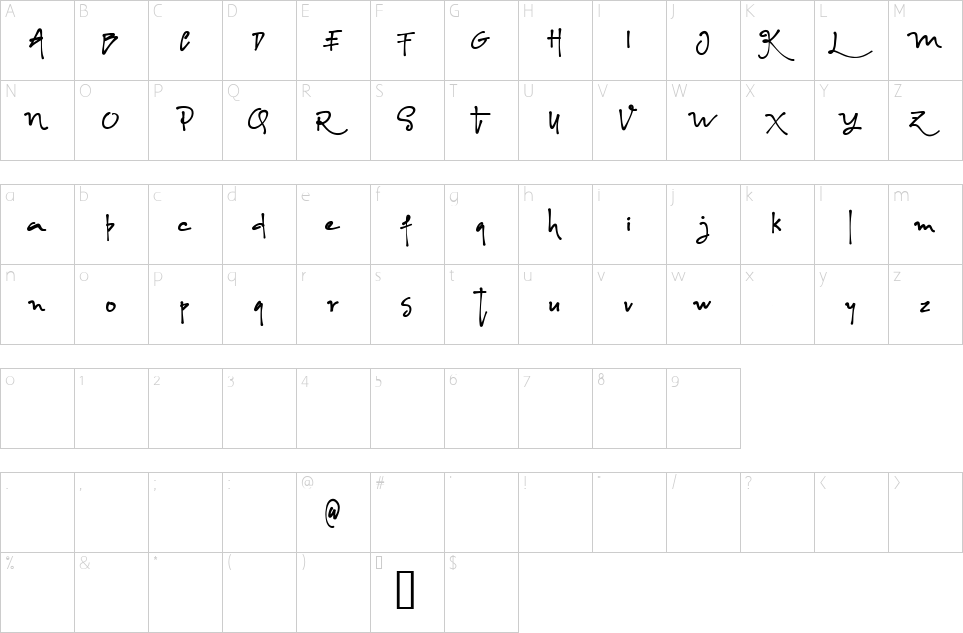
Esta fonte ‘Albanian Typeface’ foi projetada pela designer Selawe e é uma das opções gratuitas disponíveis para quem busca fontes modernas e elegantes. Com traços finos e linhas levemente arredondadas, esta fonte é adequada para diversos usos, como design de logotipo, editoração de texto em redes sociais ou qualquer projeto que precise de uma fonte de alta qualidade sem comprometer o estilo. Com a possibilidade de download para sistemas Windows e Mac, é uma escolha ideal para designers que buscam personalidade para seus trabalhos, ou simplesmente para aqueles que gostam de adicionar um toque distintivo às suas criações digitais. Com a fonte Albanian Typeface, você pode explorar a diversidade e a originalidade da tipografia, sem o custo associado às fontes pagas.